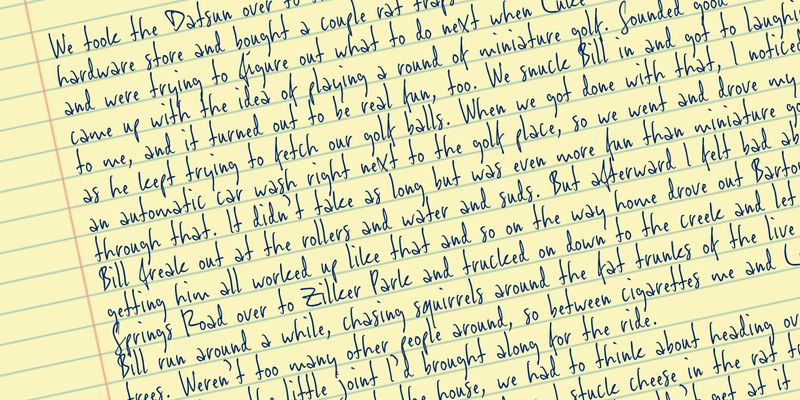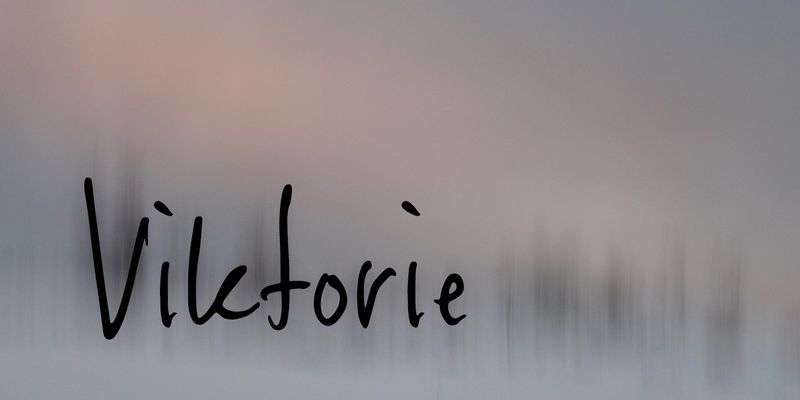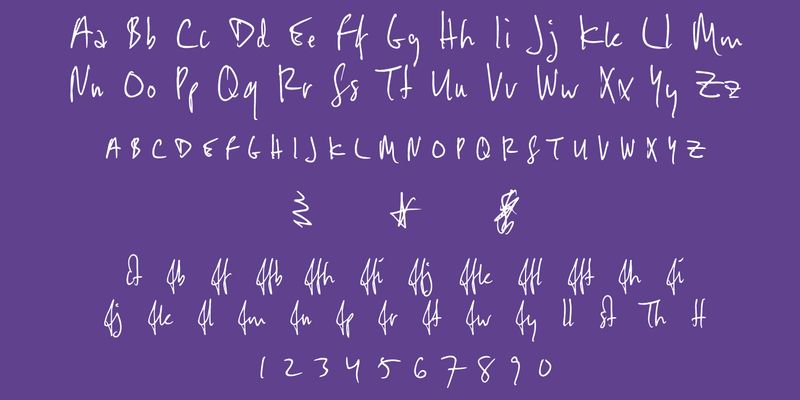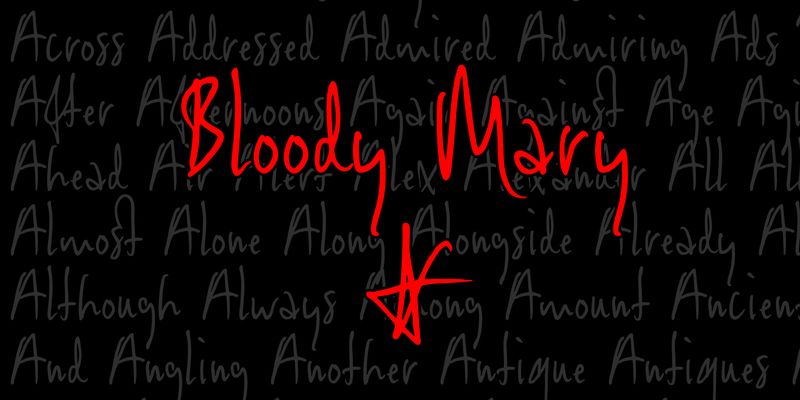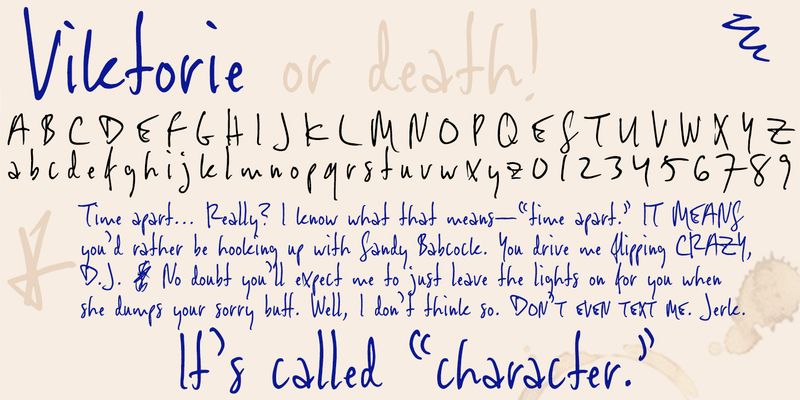
Viktorie™ könnte leicht mit der Handschrift eines eiligen Notizschreibers verwechselt werden. Seltsam lesbar und dennoch inspirierend, verfügt die Schriftart über echte Kapitälchen und volle Lateinunterstützung.